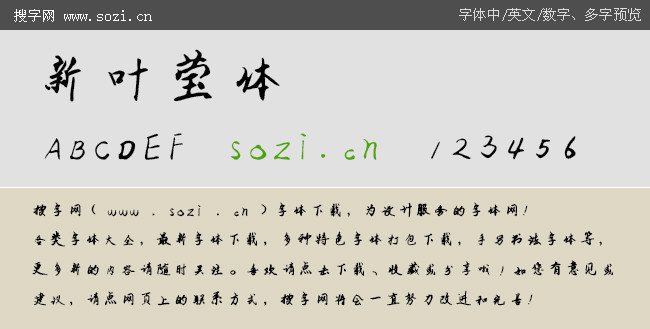
新葉瑩體
搜字網(wǎng)給大家提供一款新葉瑩體中文手寫書法字體下載,新葉瑩體由新葉傳媒制作,這副字體看上去溫柔而遒勁,一筆一畫之間抒寫著一種外柔內(nèi)剛的堅毅,橫豎撇捺之間氤氳著一絲絲的靈動,像陽光下的玉石散發(fā)著淡淡的光彩,溫和而不刺眼,寓意為“瑩”這便是字體名字的由來了!適用于包裝設(shè)計、海報設(shè)計等應(yīng)用!敬丝钭煮w可供個人非商業(yè)免費使用,商用請關(guān)注公眾號“新葉傳媒”進(jìn)行購買使用】 現(xiàn)在正值新葉瑩體推出之際,給力活動持續(xù)放映中! 1.個人包年原價29.9,現(xiàn)在只要9.9即可商業(yè)使用! 2.個人永久原價39.9,現(xiàn)在只要19.9即可商業(yè)使用! 3.企業(yè)版包年價19.9,永久商用只要69.9! 感謝漂亮帥氣的你,支持原創(chuàng)!愿新葉瑩字體陪你度過往后余生!